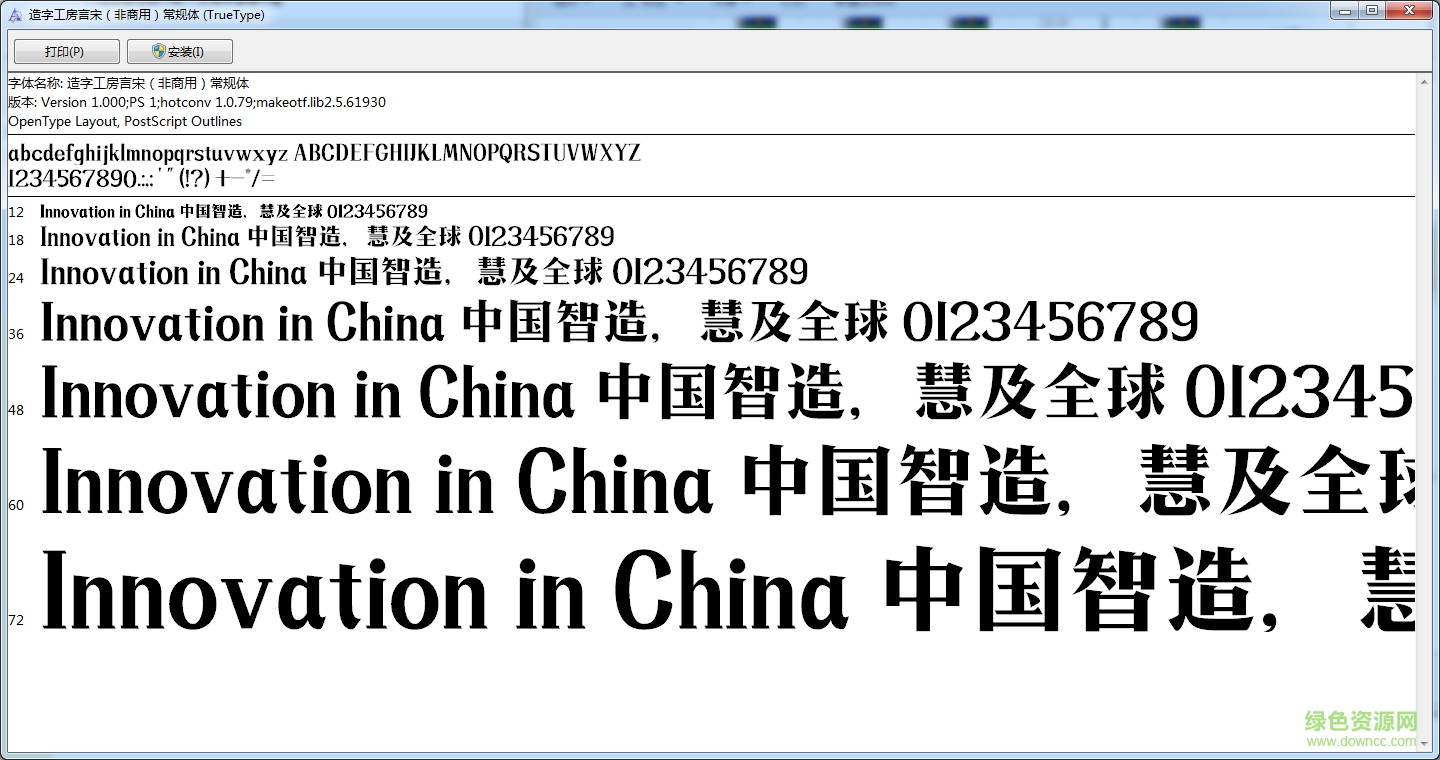
軟件介紹 軟件標簽: 造字工房言宋體 造字工房 造字工房言宋體是一款端正美觀的字體,此款字體線條粗細均勻、大小適中,結構簡單,易讀性極強,廣泛的應用于平面設計、包裝印刷、廣告設計等領域,喜歡的朋友歡迎來綠色資源網(wǎng)下載!字體安裝方法方法一:控制面板/字體/文件/安裝新字體;方法二:直接將字體復制到C:\WINDOWS\Fonts。方法三:針對win7系統(tǒng),用戶只需選中字體右鍵安裝即可。注意事項本站所有字體資源僅供個人學習與參考,如需商業(yè)使用請到相關官網(wǎng)授權。 軟件截圖 上一張下一張(1 / 1) 安裝詳細截圖 猜你喜歡 宋體字體 造字工房 宋體字體 宋體是目前最常用的一款漢字字體,宋體成型于明朝,歷史悠久,字體特點是橫細豎粗,線條平直,結構嚴謹,工整又不失大氣,非常適用于文字排版方面! 查看更多>> 原版宋體 5.37M/中文/1.4/下載 繁體宋體字體打包 14.64M/中文/2.5/免費版下載 經(jīng)典中宋繁 regular 3.26M/中文/5.0/下載 粗標宋體 2.44M/中文/5.0/下載 方太夢想宋字體(中/細/粗體) 6.36M/中文/2.5/非商用下載 宋體-亮體(chinese-gb2312) 5.85M/中文/5.0/下載 造字工房 造字工房字體是一系列簡潔美觀的字體,小編為大家?guī)砹硕嗫畛S米煮w,覆蓋了常規(guī)體、黑體、情書體等,整體效果甚是出色,全部均為ttf格式,可直接安裝導入至ps中使用,方便用戶日常使用。 查看更多>> 造字工房力黑非商用常規(guī)體ttf 766KB/中文/2.0/下載 造字工房妙妙字體 3.03M/中文/10.0/下載 造字工房丁丁手繪字體 2.86M/中文/10.0/下載 造字工房勁黑常規(guī)體 694KB/中文/2.0/下載 造字工房朗倩字體 1.07M/中文/2.9/下載 造字工房朗宋(非商用)常規(guī)體 1.00M/中文/6.6/ttf版下載 其他版本下載 標題 大小 更新日期 下載 下載地址 電腦版 造字工房言宋體字體 點擊報錯 軟件無法下載或下載后無法使用,請點擊報錯,謝謝! 關閉報錯反饋 請描述您所遇到的錯誤,我們將盡快予以修正,謝謝! *必填項,請輸入內容 本類最新 dreamweaver字體庫 首爾南山體字體 v1.06 官方版 潮字社風云簡ttf 潮字社凌渡鯤鵬簡體字體 潮字社曾玉波手書簡字體 微博慧心字體 用戶評論 熱門評論 最新評論 發(fā)表評論 查看所有評論(0) 昵稱: 請不要評論無意義或臟話,我們所有評論會有人工審核. 字數(shù): 0/500 (您的評論需要經(jīng)過審核才能顯示)